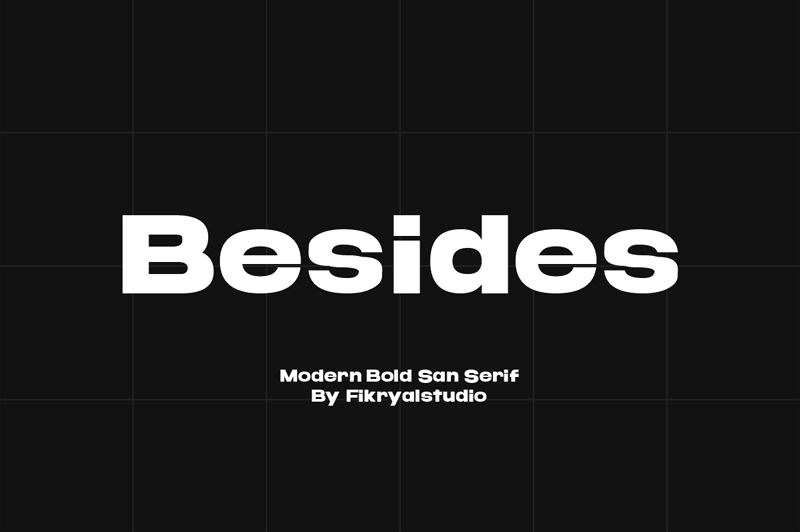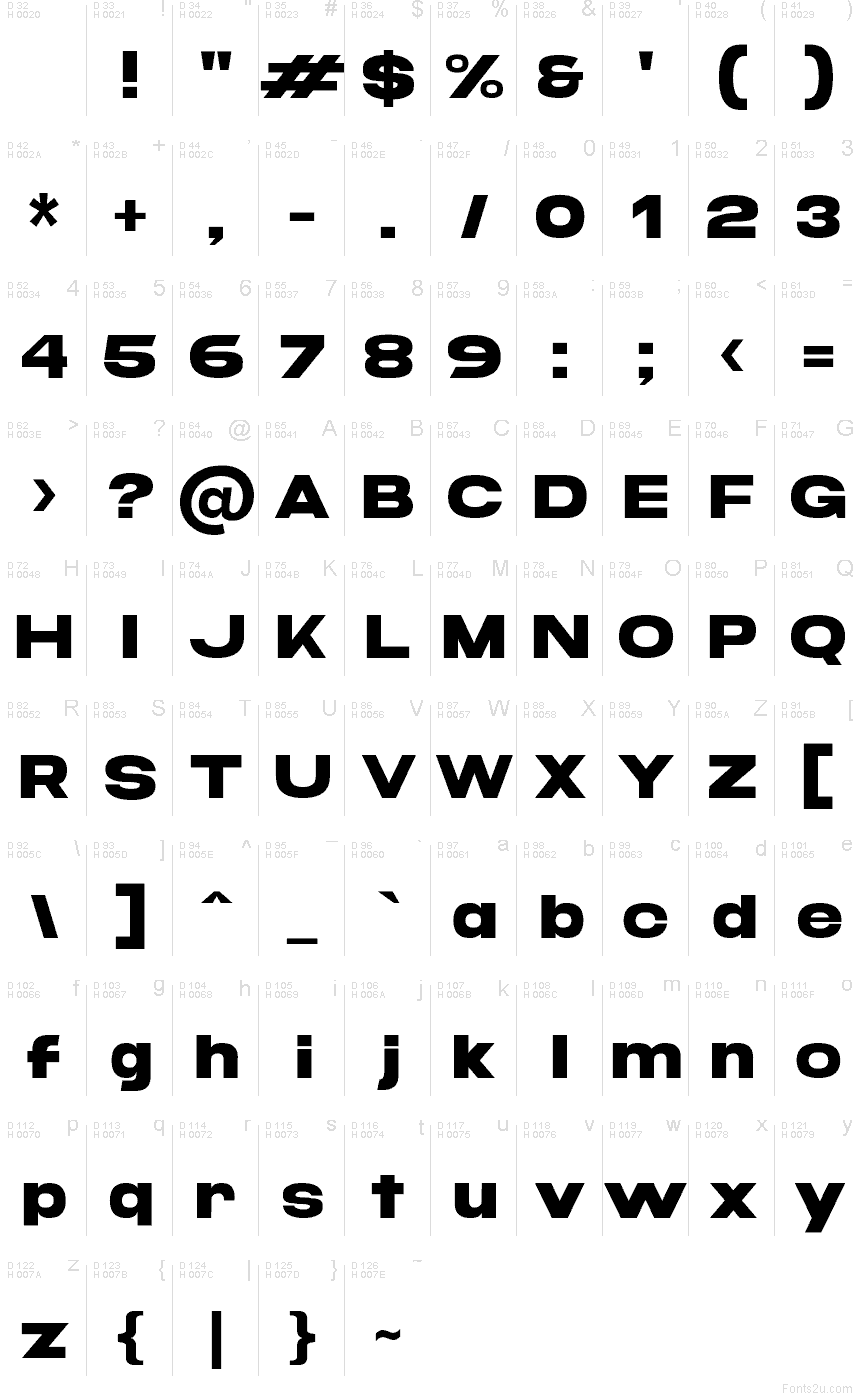
Besides, di Muhamad Fikry Nuralif di Fikryal Studio, è un font sans serif gratuito dal peso importante, con forme morbide e corpose e un ritmo serrato che ricorda l'inchiostro impresso con forza sulla carta. Le sue curve ampie e i tagli netti donano alle parole un impatto visivo sicuro e immediato, risultando accogliente anziché rigido.
Besides brilla su poster, loghi, schermate di avvio di app, miniature di YouTube, etichette di imballaggi, inserzioni social e titoli incisivi su landing page. Usalo in grandi dimensioni e concedigli un po' di respiro: la sua massa audace premia i margini generosi. Per un ottimo contrasto, abbina questo font gratuito a un grotesk leggero o a un carattere tipografico umanista.